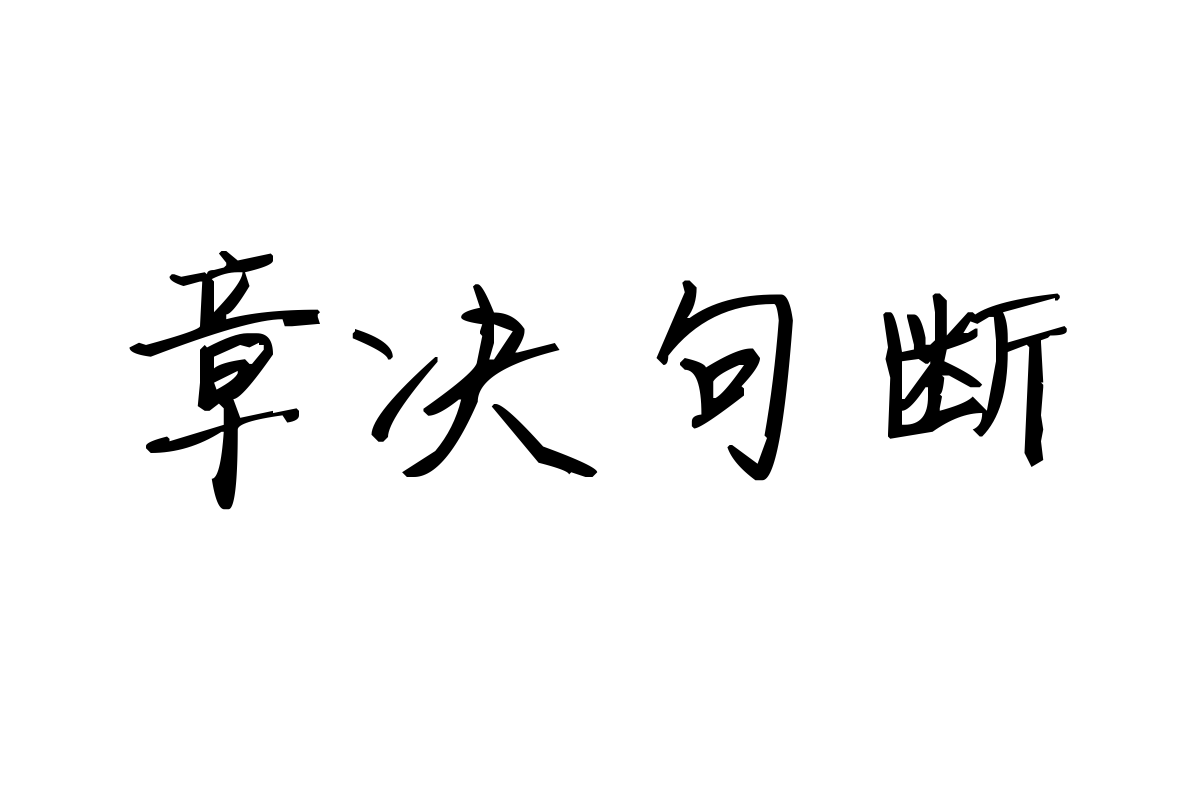
米开左耳情话字体是一款专为中文设计,具有现代感的手写风格字体。它以其独特的笔画和流畅的线条,给人一种优雅而浪漫的感觉。这款字体适用于各种场合,如广告、海报、书籍封面等,能够很好地传达出情感和氛围。
米开左耳情话字体的特点如下:
1. 笔触流畅:这款字体的笔画流畅自然,给人一种轻松愉悦的感觉。
2. 风格独特:它采用了现代手写风格,与传统的印刷字体有很大的不同。
3. 适合多种用途:无论是用于广告、海报还是书籍封面,都能展现出其独特的魅力。
4. 易于使用:这款字体的设计简单易懂,即使是初学者也能快速掌握。